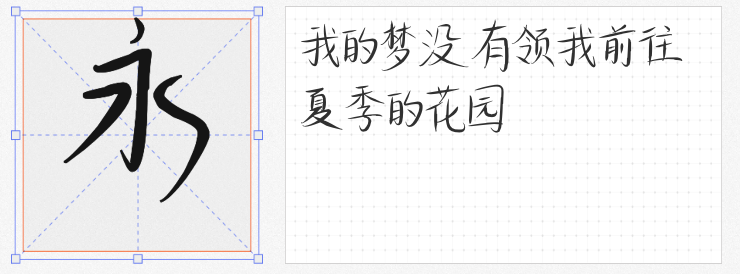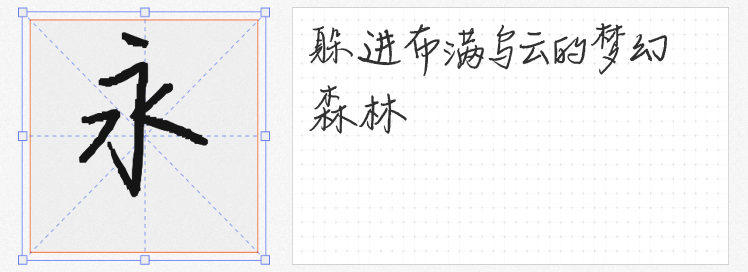
在商业设计中,手写字体以其独特的温度与个性,成为传递品牌情感的重要载体。本文精选四款特色手写字体,兼顾免费商用授权与艺术表现力,助您轻松打造兼具美感与实用性的设计作品。
1. 云峰林桥体
这款由云峰字库出品的手写字体,以工整严谨的笔触诠释"认真"二字。横平竖直间透露出书写者的专注,撇捺转折处保留自然手写痕迹。适用于教育、文化类项目的标题设计,或作为正文字体营造沉稳可靠的视觉氛围,特别适合需要传递专业感的商业场景。
2. 她屿山海
同属云峰字库的文艺系代表,字型如少女日记中的私语,带着青涩的灵动。细长的笔画搭配适度留白,在包装设计、文艺海报中能瞬间营造清新氛围。其独特的倾斜角度设计,让文字排列时产生微妙的韵律感,堪称社交媒体图文配字的理想选择。
3. 栗壳坚坚体
这款凝聚作者数月心血的字体,每个字符都承载着手写的温度。略带稚拙的笔画中透露出返璞归真的艺术气质,在咖啡厅菜单、手作产品包装等场景中能瞬间拉近与受众的距离。其独特的字间距设计,使短文案排版更具呼吸感。
4. 香蕉闻雪灵感体
以"春雪消融"为灵感的动态字体,撇捺如柳芽舒展,转角似春风拂枝。通过精密的曲线控制,实现手写质感与屏幕显示的完美平衡。在女性品牌广告、诗歌集排版等场景中,能以柔美的字形传递出盎然生机,长文本阅读时更显舒适自然。